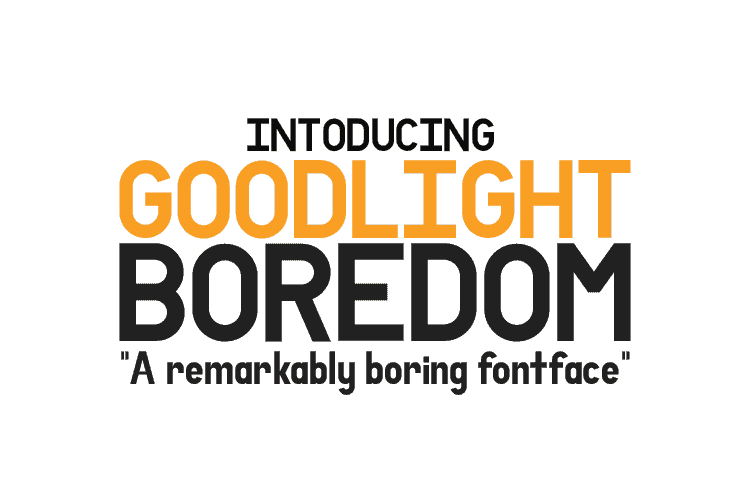
A Goodlight Boredom Font é uma tipografia sans-serif que traz à tona a essência do moderno e desconcertante mundo digital em que vivemos. Com linhas fluidas e formas elegantes, esta fonte combina a simplicidade das letras de tipo com um toque único que captura as nuances da atualidade. Ideal para aplicações digitais atuais e criativas, ela transmite uma mensagem clara e eficaz sem comprometer o estilo inovador característico do tipo sans-serif. Desenvolvida pelo designer Daler, a Goodlight Boredom Font é um recurso visual que reúne funcionalidade e arredondamento de design em uma única fonte, perfeita para usar em sites web modernos, designs gráficos contemporâneos ou qualquer projeto digital que deseja destacar-se na era do digital.